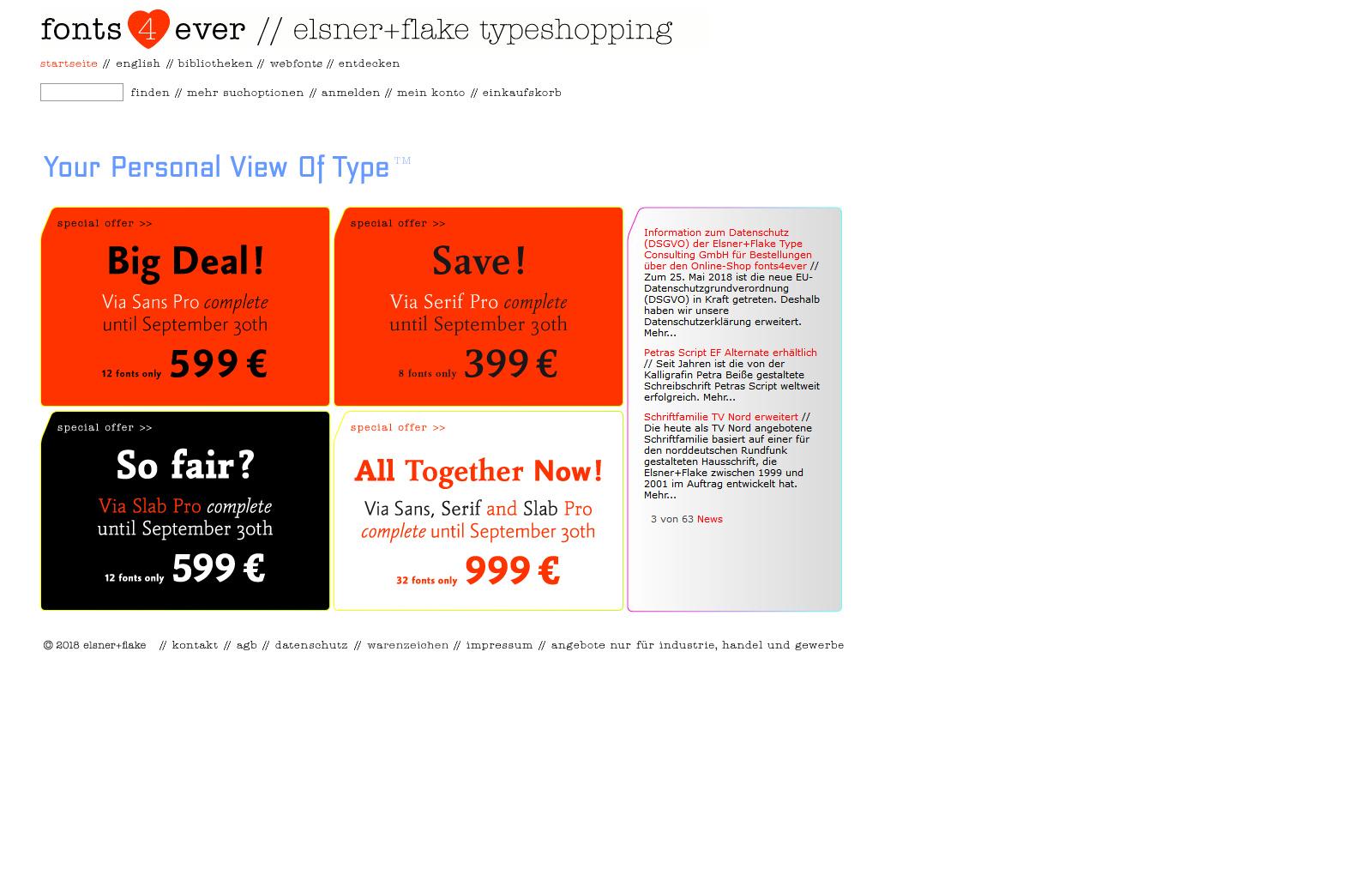
Vianova-Sippe von Jürgen Adolph
Ich bin zufällig über die von Elsner+Flake vertriebene Vianova-Familie (Serif, Slab, Sans) von Jürgen Adolph gestolpert. Da sie mir gefiel, wollte ich hier nach näheren Informationen suchen, und wundere mich, hier weder über sie noch über ihren Designer etwas zu finden.
Als Dilettant, der ich bin, frage ich mich, ob das Zufall ist, oder ob die "Eingeweihten" etwas wissen, was das Schweigen erklärt. Meine Verwunderung ist umso größer, als gerade Schriftsippen immer wieder empfohlen werden, wenn es um die Kombination mehrerer Schriften geht. (Dasselbe Schweigen herrscht übrigens bei "Font in Use".) - Wer klärt mich auf?
Achtung, Verschwörungstheorie: Liegt es daran, dass sie kein Versal-Eszett hat?
Wenn man jetzt noch das Fehlen des Bitcoin-Symbols zum Ausschlusskriterium erhebt, bleibt nicht mehr viel zu besprechen ... 😉
Ich persönlich hatte die von Dir genannten Schriftensippe bislang noch gar nicht auf dem Schirm. Auf Anhieb will sie mir nicht so richtig gefallen, das ist aber nur meine persönliche Ansicht – mir sieht sie einfach ein bisschen zu „kratzig“ aus. Alles andere (Qualität der Zurichtung, Umfang der Glyphen etc.) kann ich so spontan natürlich nicht beurteilen, da werden die Kollegen hoffentlich noch intensiver drauf eingehen. Auf alle Fälle gilt: Wenn Dir diese Schriftensippe gut gefällt, darfst Du sie jederzeit ins Wiki einpflegen – gerne mit ausführlicher Beschreibung und Nennung aller Vorteile, die sie zu bieten hat. :-D
Ich persönlich hatte die von Dir genannten Schriftensippe bislang gar nicht auf dem Schirm. Auf Anhieb gefällt sie mir nicht so richtig gut. Das ist aber nur meine persönliche Ansicht – mir sieht sie einfach ein bisschen zu „kratzig“ aus. Alles andere (Qualität der Zurichtung, Umfang der Glyphen etc.) kann ich so spontan aber natürlich nicht beurteilen, da werden die Kollegen hoffentlich noch intensiver drauf eingehen. Wenn Dir diese Schriftensippe gut gefällt, darfst Du sie jederzeit ins Wiki einpflegen – gerne mit ausführlicher Beschreibung und Nennung aller Vorteile, die sie zu bieten hat. :-D
Danke für die Auskunft und deine ästhetische Einschätzung (das 'Kratzige' kann man natürlich auch reizvoll finden)!
Ein Grund, dass die Familie noch nicht so bekannt ist, könnte das Veröffentlichungsdatum auf MyFonts sein, das mit 13. März 2018 angegeben ist. Immerhin taucht der Font aber schon auf einer Bestenliste von Luc Devroye auf, einem kanadischen Font- und Typobegeisterten – im Hauptberuf Informatiker, übrigens auch an einer Hochschule (the best commercial typefaces of 2018: Luc’s selection  – so im oberen Drittel der Seite).
In der Beschreibung auf MyFonts steht doch schon einiges über die Entstehungsgeschichte und über den Entwerfer, der nach der Entwicklung des Fonts im Studium einem guten Rat gefolgt ist und dann offenbar eine solide Karriere im Corporate Design Bereich hingelegt hat – da passt der Font auch ganz gut hin. (Günter Gerhard Lange: „Not bad what you are doing there. But if you want to make a living with this, you might as well order your coffin now.“ Wie recht er hat.)
Eine solche stilübergreifende Schriftfamilie ist eine ehrgeizige Unternehmung und passt gut in Corporate-Design-Zusammenhänge, bekannteste Vertreter sind die Corporate A-S-E von Weidemann und die Compatil von Olaf Leu, wobei die Compatil auch noch die Eigenschaft hat, dass Lettern stilübergreifend dieselbe Dickte aufweisen.